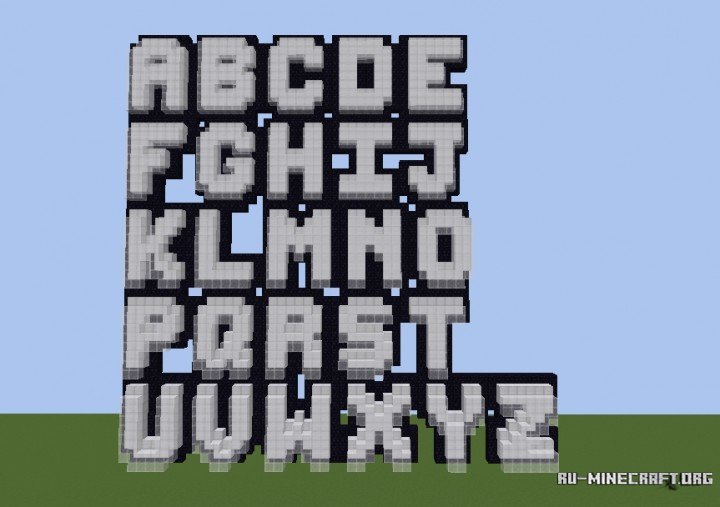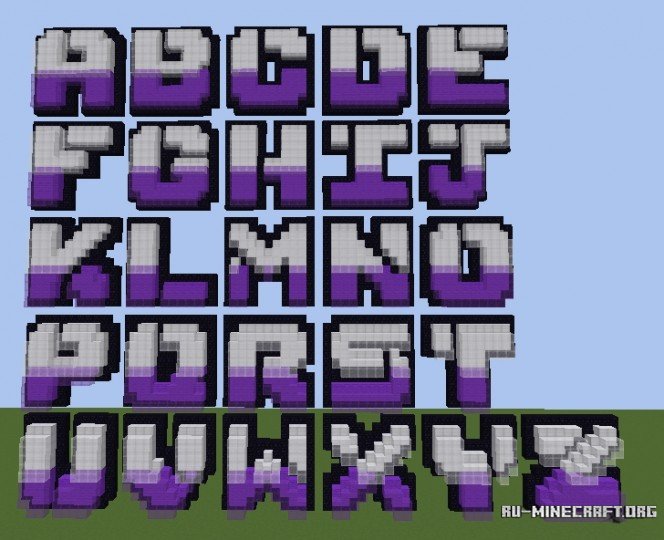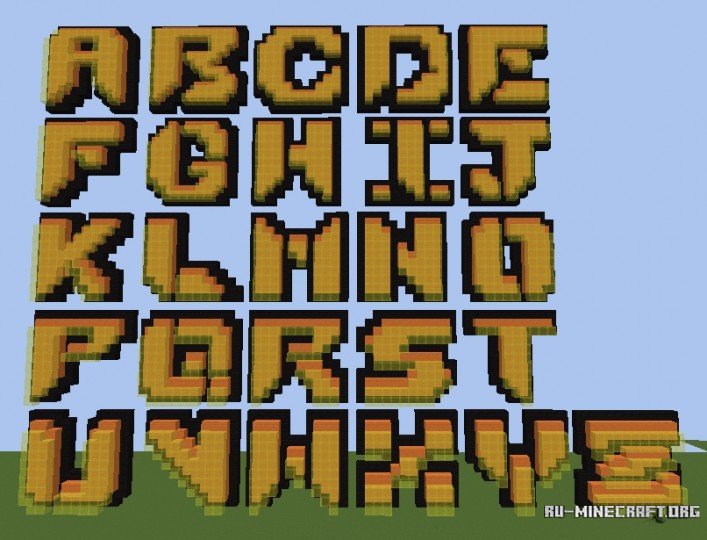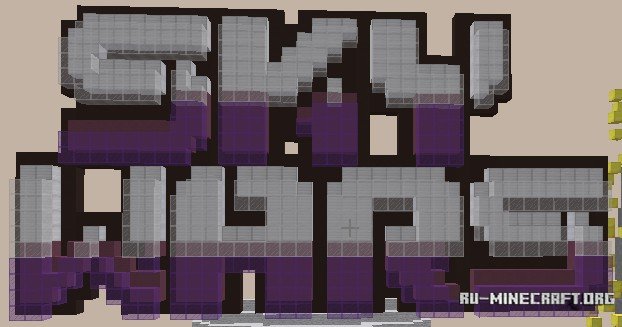
Скачать Server Logo Fonts для Minecraft
Интересная карта, под названием - Server Logo Fonts, которая представляет из себя своеобразный набор шрифтов, которые сможете использовать при составлении какой-либо надписи, например название вашего сервера, или просто какую-либо свободную надпись, которую будут видеть все игроки вашего сервера...